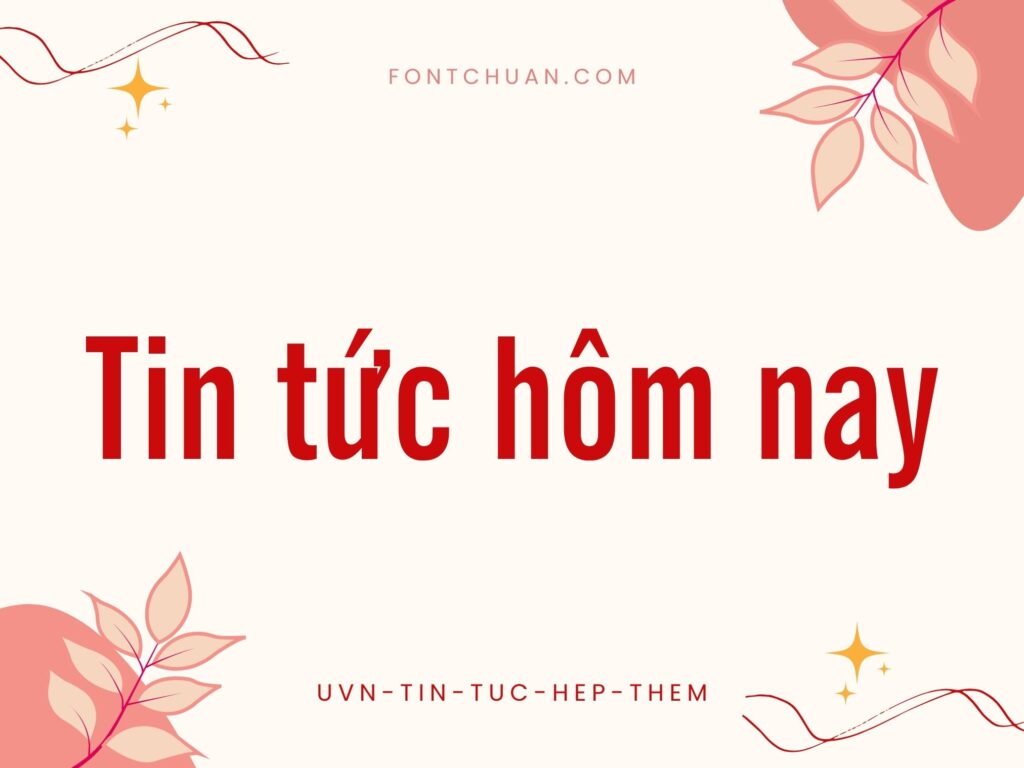
Font UVN Tin Tuc Hep Them Việt Hóa
UVN Tin Tức Hẹp Thêm là phiên bản thu gọn tối đa chiều ngang trong dòng UVN Tin Tức, thích hợp cho những thiết kế cần tiết kiệm không gian nhưng vẫn giữ được sự tinh gọn và chuyên nghiệp. Với phong cách sans-serif hiện đại và cấu trúc tối ưu hóa cho hiển thị trên các nền kỹ thuật số, font này trở thành công cụ hữu ích trong trình bày nội dung nhiều dòng hoặc giao diện dày đặc chữ. Khi kết hợp cùng Font Monospace, UVN Tin Tức Hẹp Thêm mang lại sự đối lập thú vị giữa nét gọn gàng hẹp ngang và sự ổn định kỹ thuật, giúp thiết kế thêm phần linh hoạt và chuyên nghiệp. Font này chỉ được sưu tầm và đăng bởi thành viên của Font Chuẩn, nhằm đáp ứng nhu cầu thiết kế đa dạng, sáng tạo trong môi trường làm việc thực tế của các nhà thiết kế.
Font sở hữu các ký tự có độ rộng siêu hẹp, khoảng cách chữ được cân chỉnh khéo léo giúp vẫn đảm bảo khả năng đọc tốt. Thiết kế này rất phù hợp với các bảng biểu, giao diện app, hệ thống dashboard hoặc thiết kế đồ họa kỹ thuật số. Nhờ sự rõ ràng và trực quan, UVN Tin Tức Hẹp Thêm đặc biệt phù hợp với các ngành nghề như công nghệ, giáo dục, quảng cáo và truyền thông. Font cũng có thể ứng dụng tốt trong các sự kiện như Tết, lễ hội, sinh nhật hoặc ngày Nhà giáo.